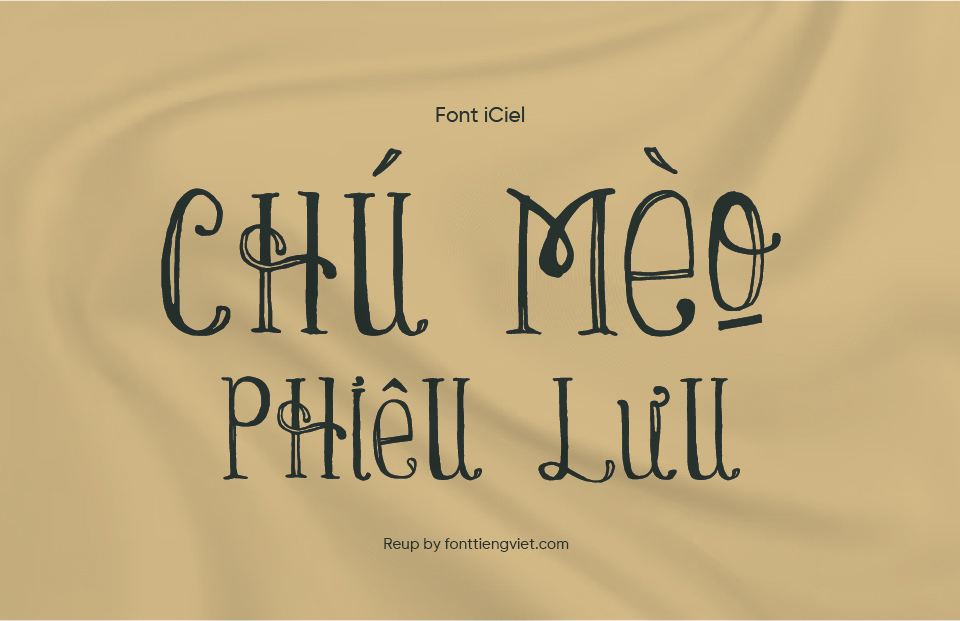
Font Việt hóa iCiel Lady Rene
Khám phá sức hút cổ điển từ Font Việt hóa iCiel Lady Rene trong thiết kế đồ họa
Trong thế giới đồ họa hiện đại, việc tìm kiếm một Font Miễn Phí mang phong cách vẽ tay thủ công là điều vô cùng cần thiết để tạo nên dấu ấn riêng biệt. Font Việt hóa iCiel Lady Rene chính là một viên ngọc quý dành cho những ai yêu thích vẻ đẹp cổ điển, lãng mạn và đầy chất thơ. Được thiết kế bởi Laura Warsshauer, bộ phông chữ này mô phỏng nét bút mực tinh tế, mang lại cảm giác ấm cúng và gần gũi cho mọi tác phẩm nghệ thuật.
Đặc điểm nổi bật của Font Việt hóa iCiel Lady Rene
Điểm làm nên sự khác biệt của bộ chữ này chính là những đường nét không hoàn hảo một cách cố ý, tạo nên sự tự nhiên như được viết trên giấy thật. Khi sử dụng Font Việt hóa iCiel Lady Rene, bạn sẽ nhận thấy các ký tự có độ bay bổng và linh hoạt cao, cực kỳ phù hợp cho các chủ đề về thiệp cưới, thực đơn nhà hàng hoặc bìa sách nghệ thuật. Đội ngũ iCiel đã tinh chỉnh kỹ lưỡng các dấu tiếng Việt để đảm bảo tính thẩm mỹ cao nhất cho người dùng Việt Nam.
Ứng dụng thực tế trong giáo dục và đời sống
Đối với các bạn học sinh và giáo viên, bộ font này là công cụ tuyệt vời để trang trí bảng tin, thiết kế bài thuyết trình hoặc làm thiệp chúc mừng thầy cô. Sự mềm mại của nó giúp thông điệp trở nên nhẹ nhàng và dễ đi vào lòng người hơn. Ngoài ra, các nhà thiết kế tự do cũng thường xuyên sử dụng nó để xây dựng bộ nhận diện thương hiệu cho các cửa hàng handmade hoặc tiệm bánh ngọt.